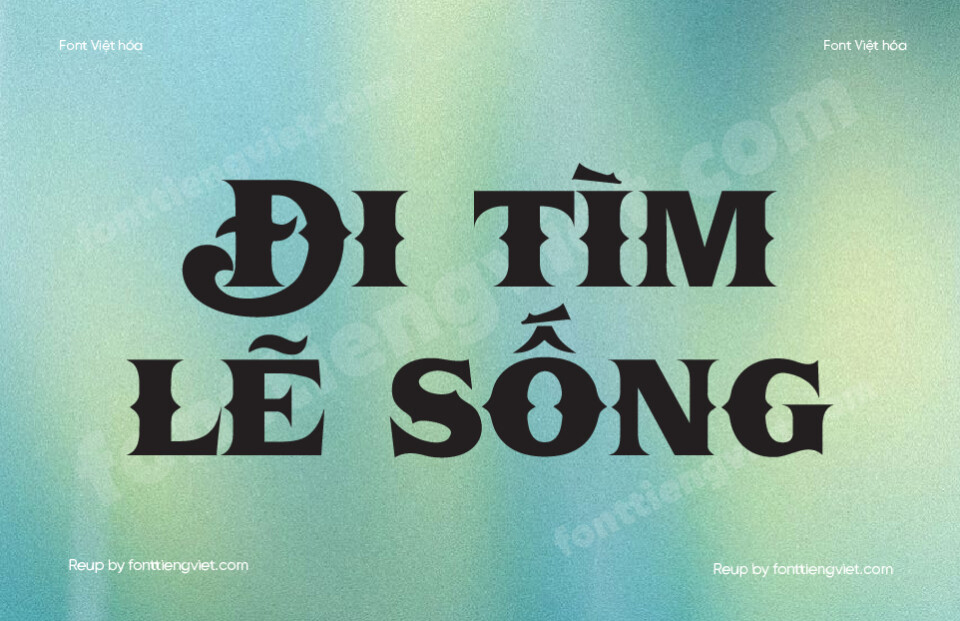
Font Việt hóa UTM Boston K&T – Font Việt hóa vintage: Nét đẹp cổ điển cho thiết kế hiện đại
Giới thiệu về Font Việt hóa UTM Boston K&T – Font Việt hóa vintage
Trong thế giới đồ họa, việc lựa chọn một Font Chữ phù hợp đóng vai trò quyết định đến linh hồn của tác phẩm. Font Việt hóa UTM Boston K&T – Font Việt hóa vintage là một lựa chọn hoàn hảo cho những ai đang tìm kiếm sự hoài cổ, tinh tế và sang trọng. Đây là bộ font được cộng đồng thiết kế tại Việt Nam ưa chuộng nhờ khả năng truyền tải cảm xúc mạnh mẽ thông qua từng đường nét đậm chất retro. Với sự tỉ mỉ trong quá trình Việt hóa, các dấu câu và ký tự tiếng Việt được xử lý mượt mà, giúp người dùng không còn lo lắng về lỗi hiển thị khi soạn thảo văn bản hay làm tiêu đề.
Đặc điểm nổi bật của Font Việt hóa UTM Boston K&T – Font Việt hóa vintage
Phong cách thiết kế độc đáo
Font Việt hóa UTM Boston K&T – Font Việt hóa vintage sở hữu cấu trúc chữ chắc chắn nhưng không kém phần mềm mại. Những đường nét uốn lượn đặc trưng gợi nhớ về các bảng hiệu quảng cáo thập niên 80-90. Điều này giúp bộ font trở nên lý tưởng cho các dự án thiết kế bao bì, thực đơn nhà hàng hoặc các bìa sách mang tính giáo dục lịch sử.
Tính ứng dụng đa dạng trong đời sống
Không chỉ dùng trong in ấn, font chữ này còn hoạt động tốt trên các nền tảng kỹ thuật số như banner website hay ảnh bìa mạng xã hội. Nhờ độ tương phản cao và tính thẩm mỹ vượt trội, nó giúp nội dung trở nên nổi bật và thu hút thị giác của người xem ngay từ cái nhìn đầu tiên.
Kết luận và trải nghiệm Font Việt hóa UTM Boston K&T – Font Việt hóa vintage